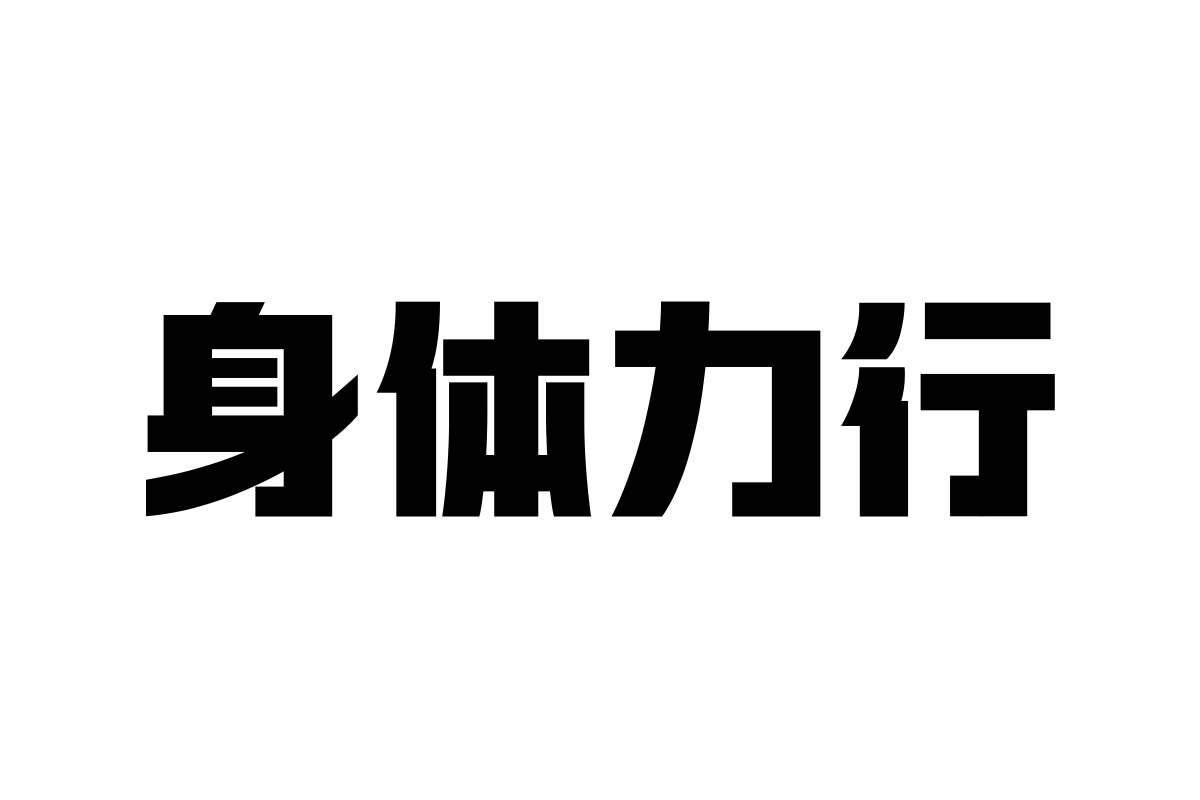
上首壹方体字体是一款具有独特风格的中文字体。它的设计灵感来源于中国传统的书法艺术,结合了现代审美观念和创意思维,打造出一款既具有传统文化韵味又不失现代感的字体。
上首壹方体字体的特点如下:
1. 字形结构:该字体采用了传统的汉字结构,包括笔画、部首、偏旁等元素。每个字符都经过精心设计,使得整体字形更加和谐、美观。
2. 笔画流畅:上首壹方体字体的笔画流畅自然,没有过多的装饰性细节,使得整个字体看起来简洁、大方。
3. 风格独特:该字体融合了传统与现代的元素,既有古典的韵味,又不失时尚感。它适合用于各种场合的文字设计,如广告、海报、书籍封面等。
4. 可读性强:上首壹方体字体的字形规整、清晰,易于阅读和识别。无论是在印刷还是电子屏幕上,都能保持良好的视觉效果。
5. 适用范围广泛:该字体适用于各种文字设计领域,如品牌标识、产品包装、宣传册、网页设计等。无论是商业还是艺术类的设计作品,都能展现其独特的魅力。
总之,上首壹方体字体是一款具有独特风格的中文字体,适合用于各种文字设计领域。它融合了传统与现代的元素,既保留了中华文化的精髓,又展现了现代审美观念的创新精神。